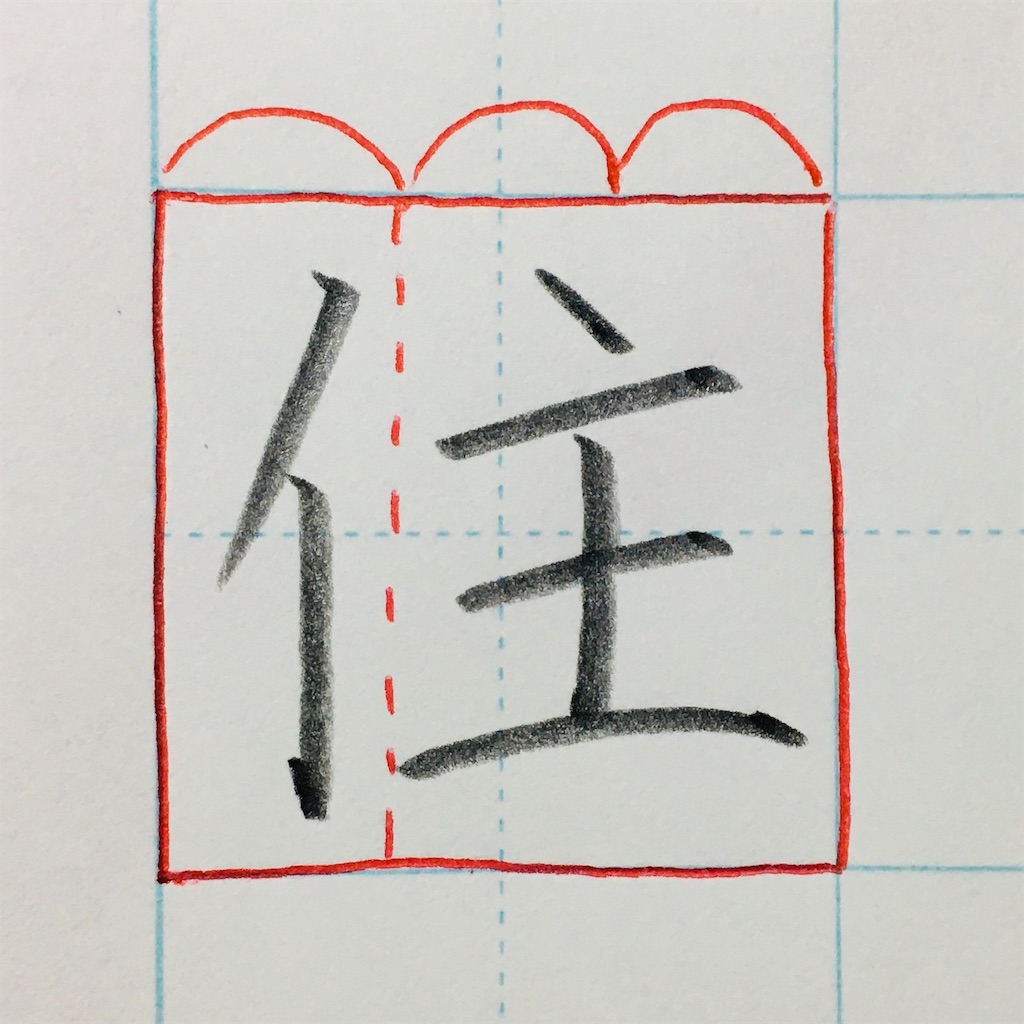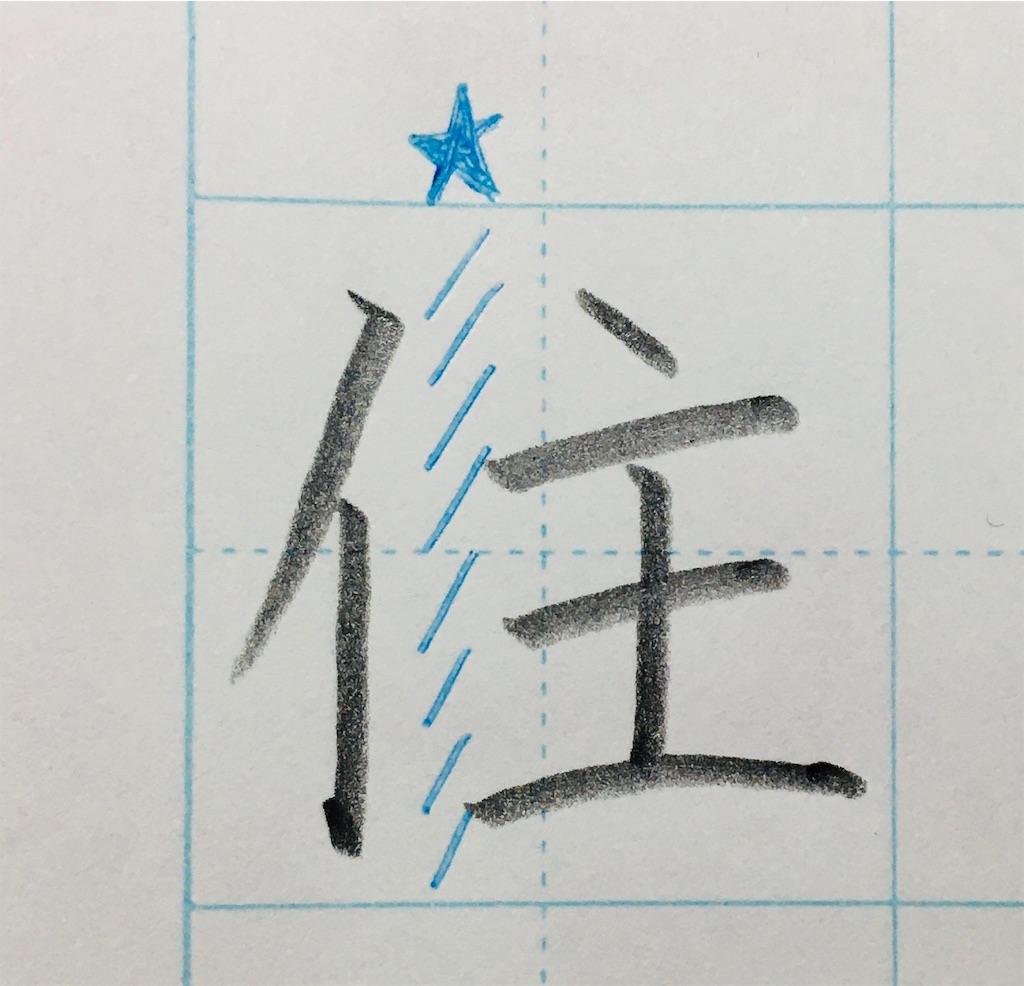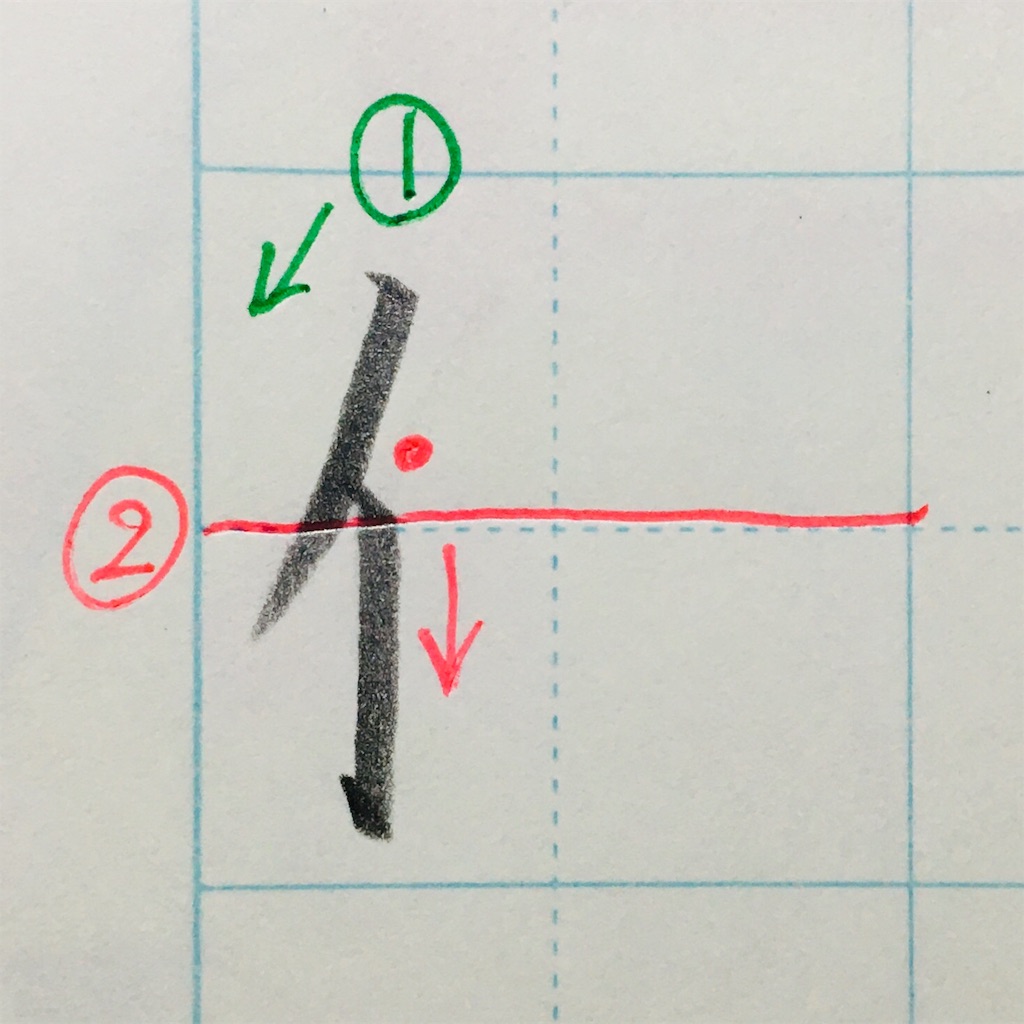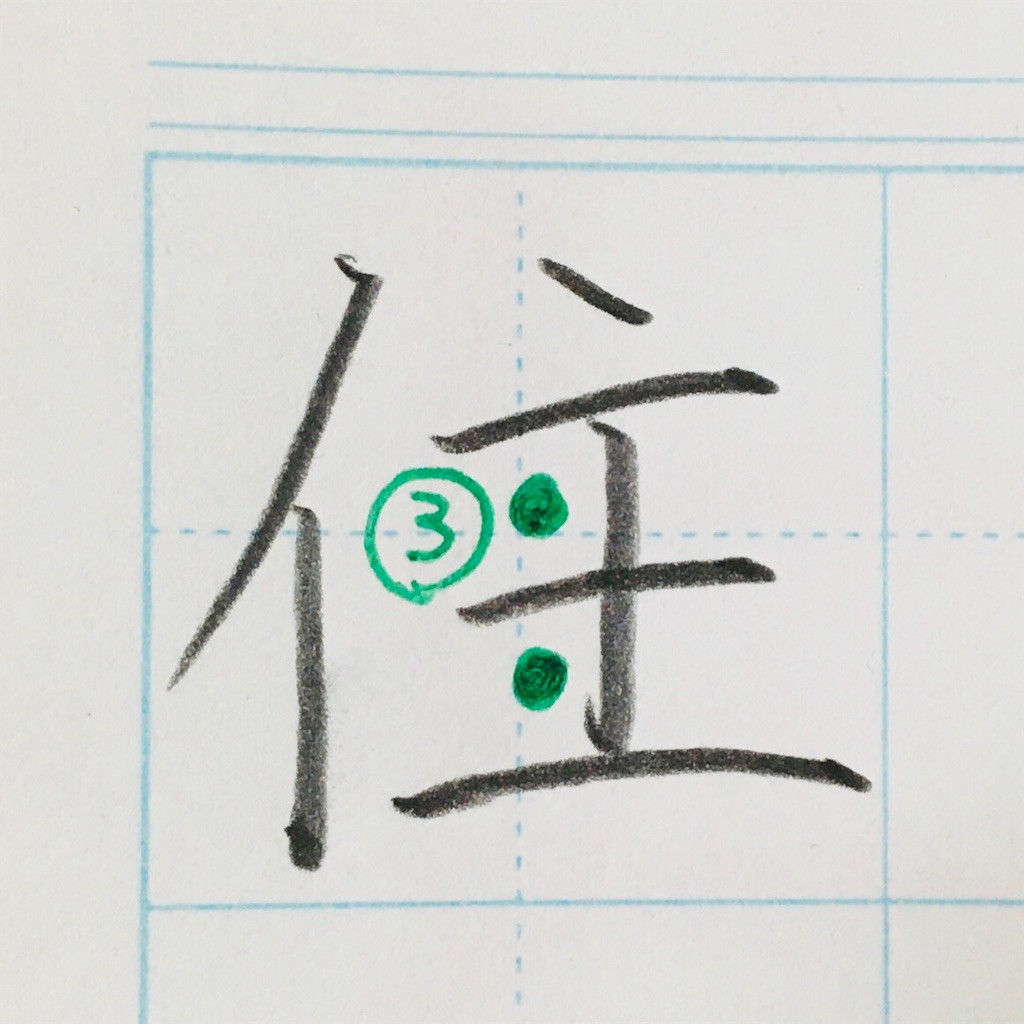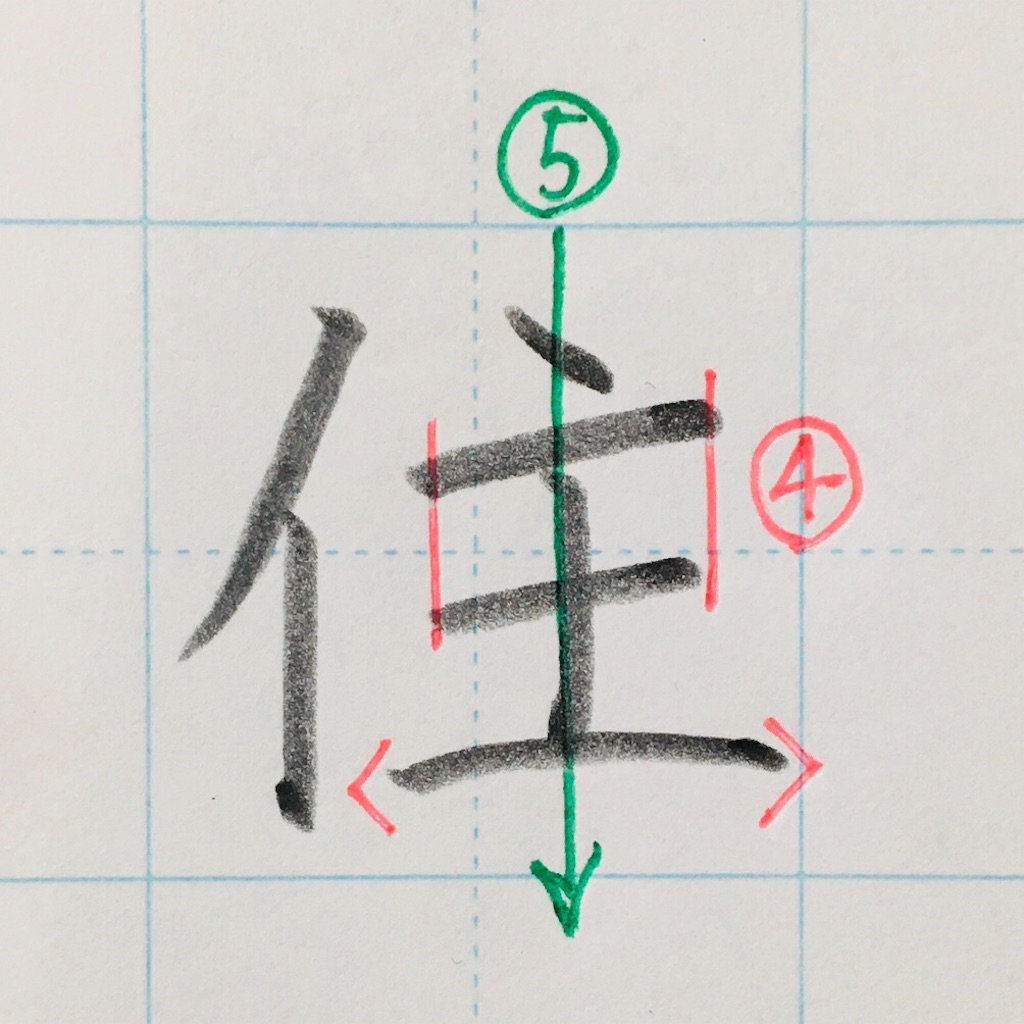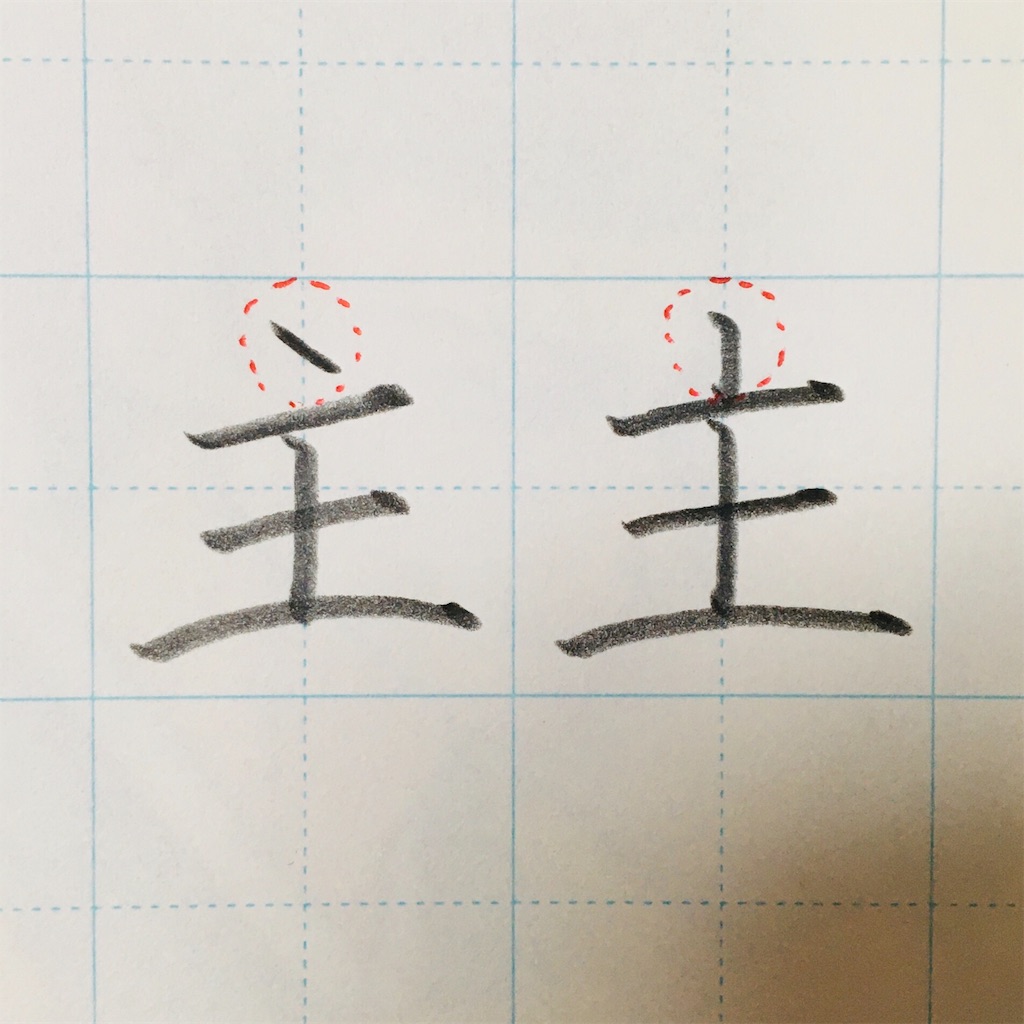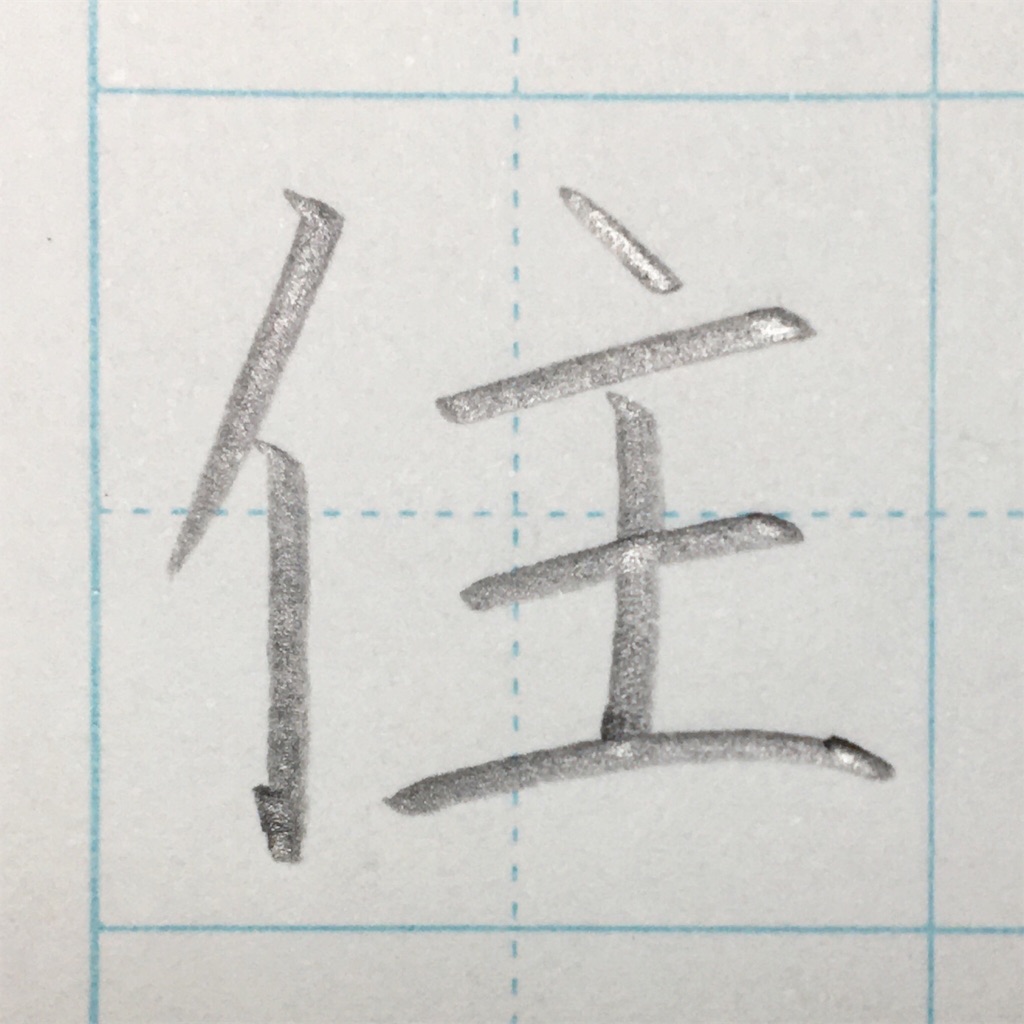
今回は「住」の書き方を解説します。
「住」のきれいな書き方
「住」の細かいポイント
①1画目は30°くらいで払います。
②2画目は半分より少し上から。まっすぐに。
私はよく〇〇という表現を使いますが、角度の確認、感覚を身につけるためにも、はじめはマス目を使った練習がオススメです!
45°だと、こんな感じ。マス目の対角線使って。
図形のように、何となく角度を覚えておくと迷わずに書くことができます。
③間を等しく。
④4画目、6画目は同じ長さ、
7画目は長く強調。
(少し反ると◎!)
⑤「てん」から、5画目の縦画は
まっすぐに通す。
「てん」は、斜め(45°位)でも、
まっすぐでもOK。お好みで(^-^)